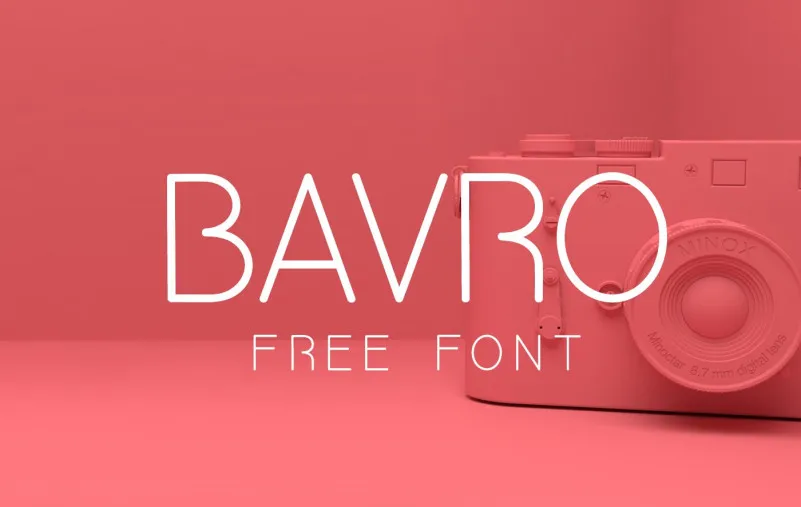
Bavro Free Font é uma fonte sans-serif inspirada numa estética minimalista e geométrica, criada pela Twicolabs Fontdation. Esta elegante fonte em all caps oferece alternativas estilizadas que se adequam perfeitamente a múltiplas aplicações, como banners, anúncios, logomarcas, revistas, moda e outros projetos visuais. Ideal para quem busca uma fonte moderna e minimalista para dar vida às suas criações gráficas, esta fonte se destaca por sua simplicidade e linhas geométricas puras. É perfeita tanto para designers de sites quanto para profissionais da comunicação visual em geral que buscam um recurso visual fresco e contemporâneo.